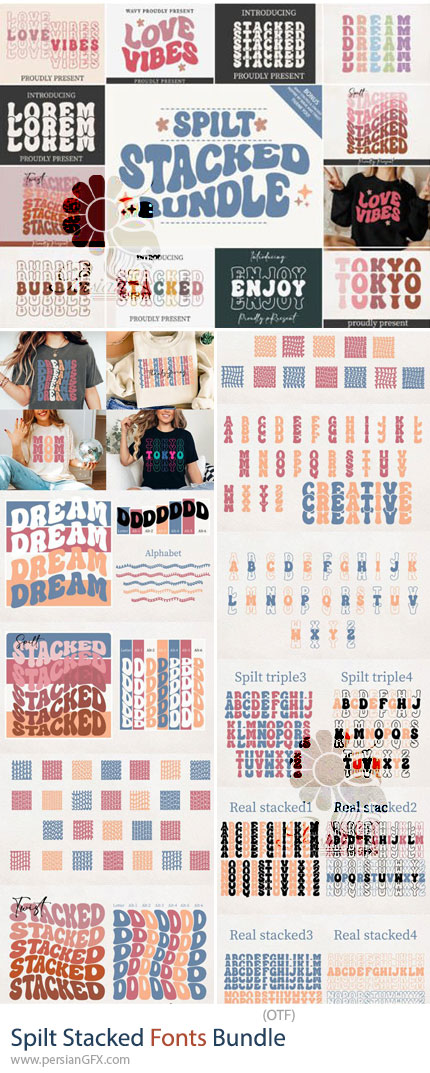
در این بخش شاهد مجموعه فونت انگلیسی چند ردیفه و لایهای برای طراحی حرفهای می باشید که با فرمت OTF بر روی سایت برای دانلود قرار گرفته است. Spilt Stacked Fonts Bundle یک مجموعه فونت خلاقانه با سبک Stacked ،Layered و Retro Display است که برای ایجاد نوشتههای خاص، تایپوگرافیهای جذاب و طرحهای گرافیکی مدرن طراحی شده است. این فونت با ساختار لایهای و ظاهر موجدار، امکان ایجاد متنهایی متفاوت و چشمگیر را برای پروژههای طراحی فراهم میکند. این مجموعه انتخابی عالی برای طراحانی است که به دنبال ساخت لوگو، پوستر، طرحهای تبلیغاتی، بستهبندی، طراحی لباس، کارت دعوت و محتوای شبکههای اجتماعی با حس و حال وینتیج، گرافیکی و هنری هستند. Spilt Stacked Fonts Bundle یک مجموعه فونت جذاب برای طراحانی است که میخواهند متنهای معمولی را به طرحهای گرافیکی خاص و حرفهای تبدیل کنند. ظاهر لایهای، سبک رترو و فرمهای خلاقانه این فونت، آن را به گزینهای مناسب برای طراحی لوگو، پوستر، برندینگ، محصولات چاپی و پروژههای تبلیغاتی تبدیل کرده است.
کاربردهای این مجموعه:
- طراحی لوگو و لوگوتایپ
- طراحی لباس و محصولات چاپی
- پوسترهای تبلیغاتی
- کاور موسیقی و آلبوم
- طراحی پست و استوری شبکههای اجتماعی
- بستهبندی محصولات
- تایپوگرافی هنری
- طراحی کارت، دعوتنامه و پروژههای خلاقانه
مناسب برای:
- طراحان گرافیک
- طراحان لوگو و برندینگ
- تصویرگران دیجیتال
- طراحان چاپ
- تولیدکنندگان محتوای بصری
- طراحان محصولات و Merchandise